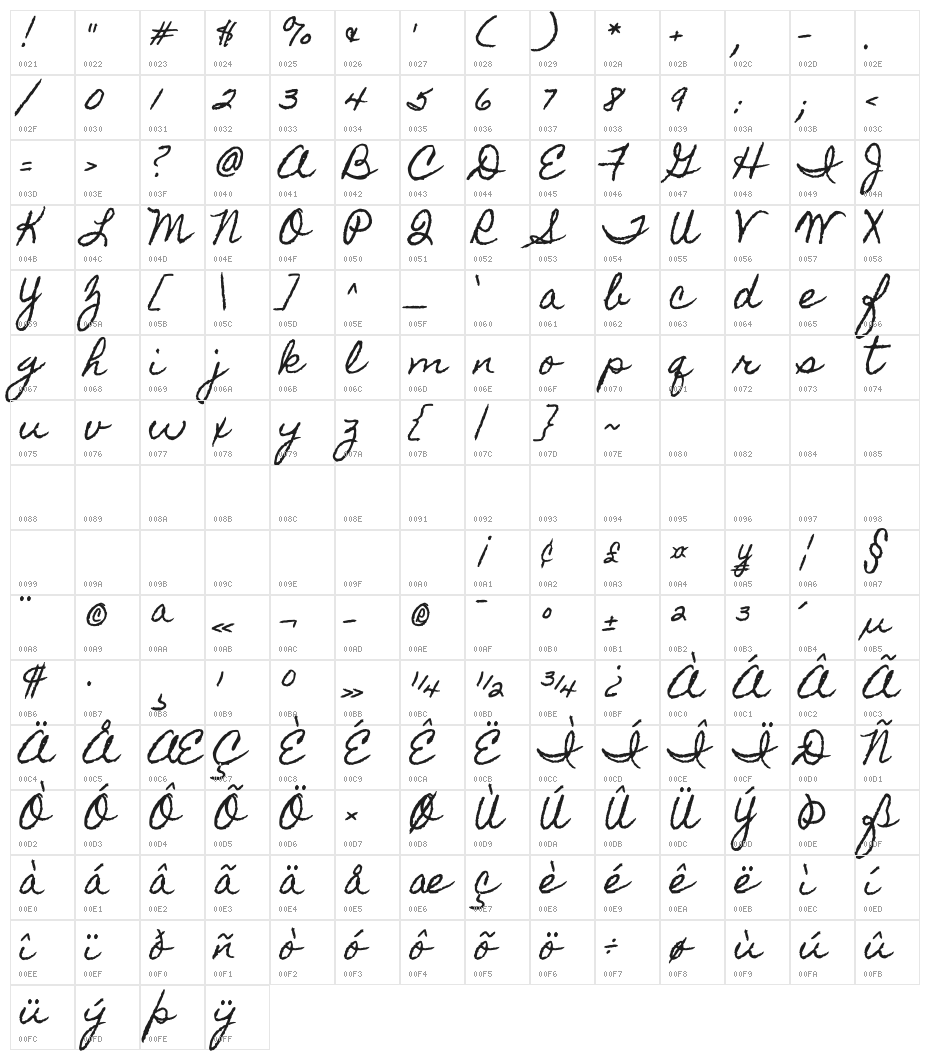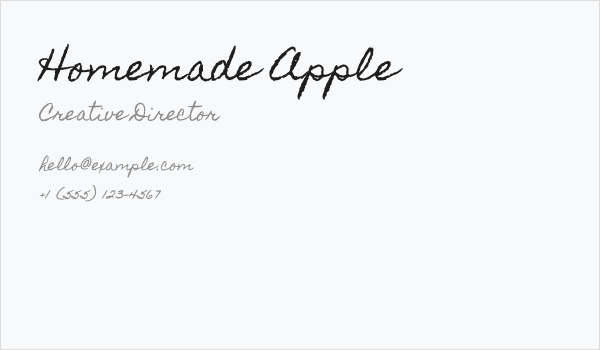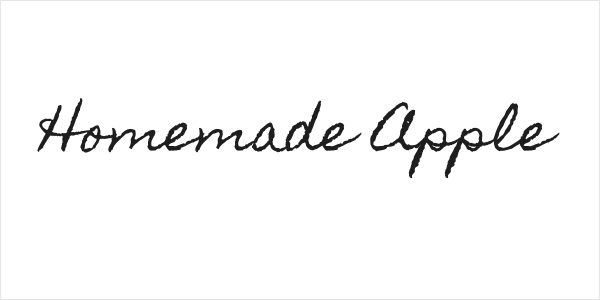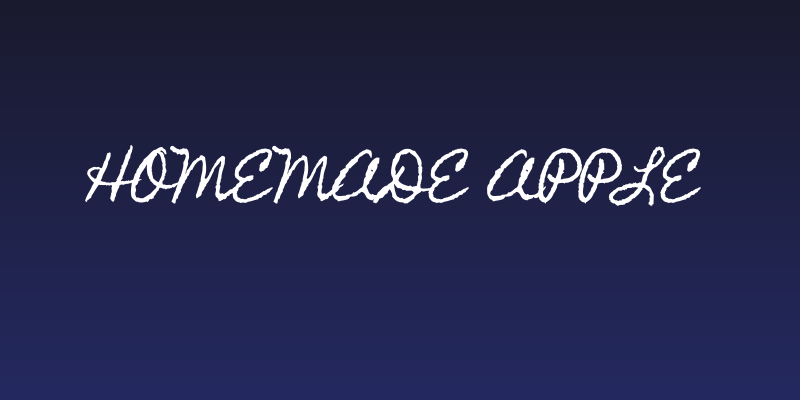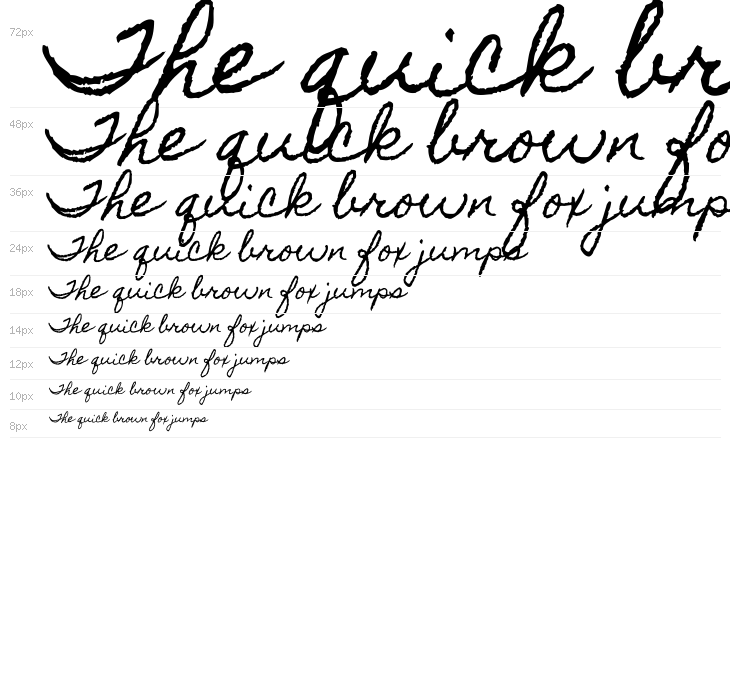
Homemade Apple Font
| Gesamtstil | Casual, Personal |
| Anwendungsfall | Invitations, Greeting cards, Personal notes |
| Vorgeschlagene Projekte | Ideal for invitations, greeting cards, personal notes, and creative branding. |